Lateinamerika
Zwischen dem Hochland der Anden, dem Yucatán-Dschungel und den Pampas Argentiniens entstanden über Jahrtausende ganz unterschiedliche Wege, Sprache sichtbar zu machen — von den Glyphen der Maya bis zum lateinischen Alphabet der Kolonialzeit.
Die Maya-Schrift ist die am besten erforschte indigene Schrift Amerikas — eine komplexe Verbindung aus Logogrammen und Silbenzeichen, gemeißelt in Stein und gemalt in Codices. Die aztekischen Bildhandschriften erzählten Geschichte, Tribut und Rituale in farbigen Szenen mit Lautandeutungen. Die Inka wählten einen anderen Weg: Ihre Quipus verwendeten Knoten an Schnüren als Aufzeichnungssystem für Zahlen und Erzählungen.
Mit den Konquistadoren kam das lateinische Alphabet — und mit ihm wurden viele indigene Sprachen erstmals nach europäischem Muster verschriftlicht. Heute leben beide Erbschaften nebeneinander.
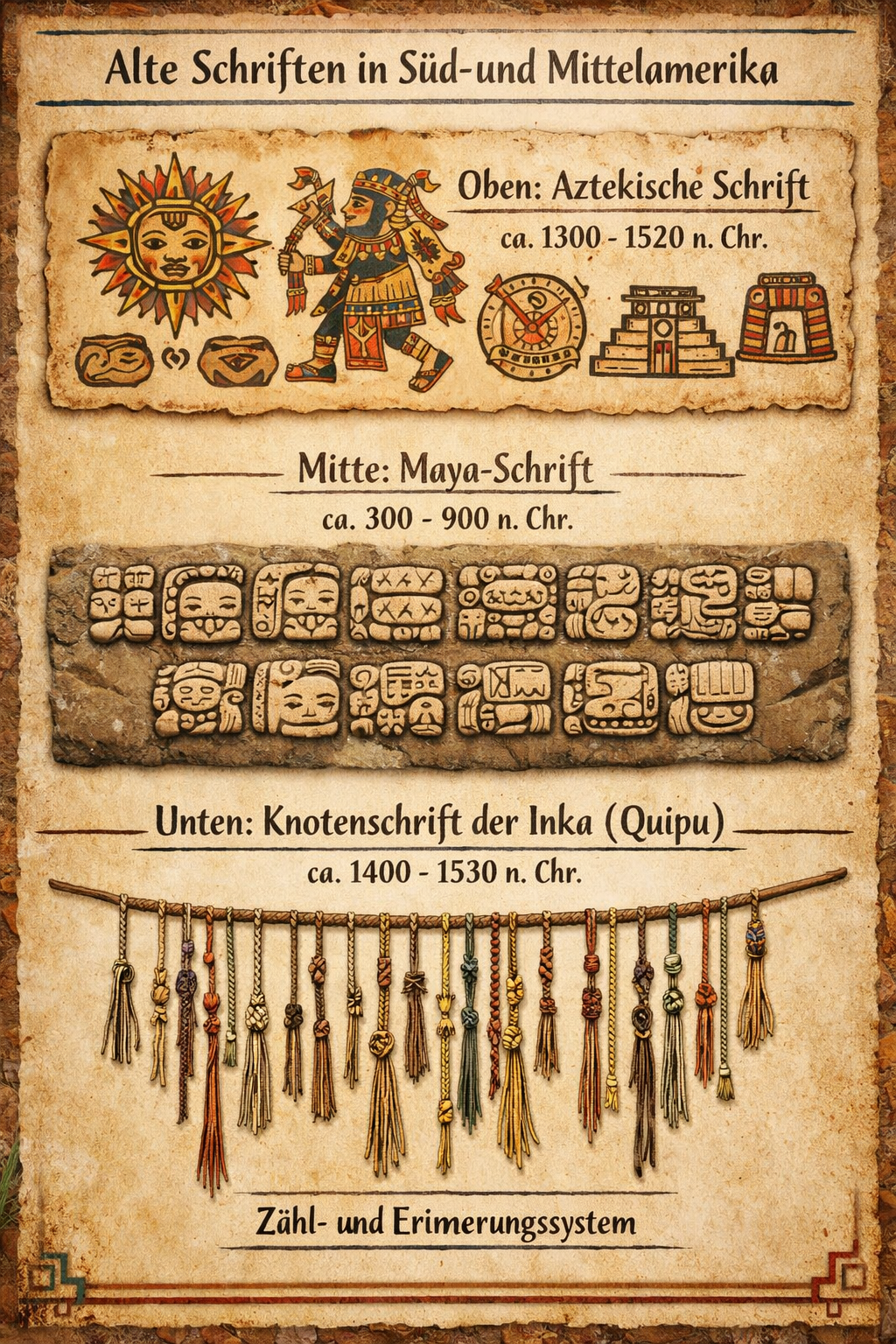
Anden, Maya, Pampas
Schriftspuren in Süd- und Mittelamerika
Vom Rio Grande bis Feuerland
Die Karte legt die Schriftlandschaft Süd- und Mittelamerikas frei: Maya- und Aztekenreich im Norden, Inka-Reich entlang der Anden, dazu zahllose kleinere Schriftgemeinschaften — und überall die nachträglichen Spuren der iberischen Kolonialzeit.